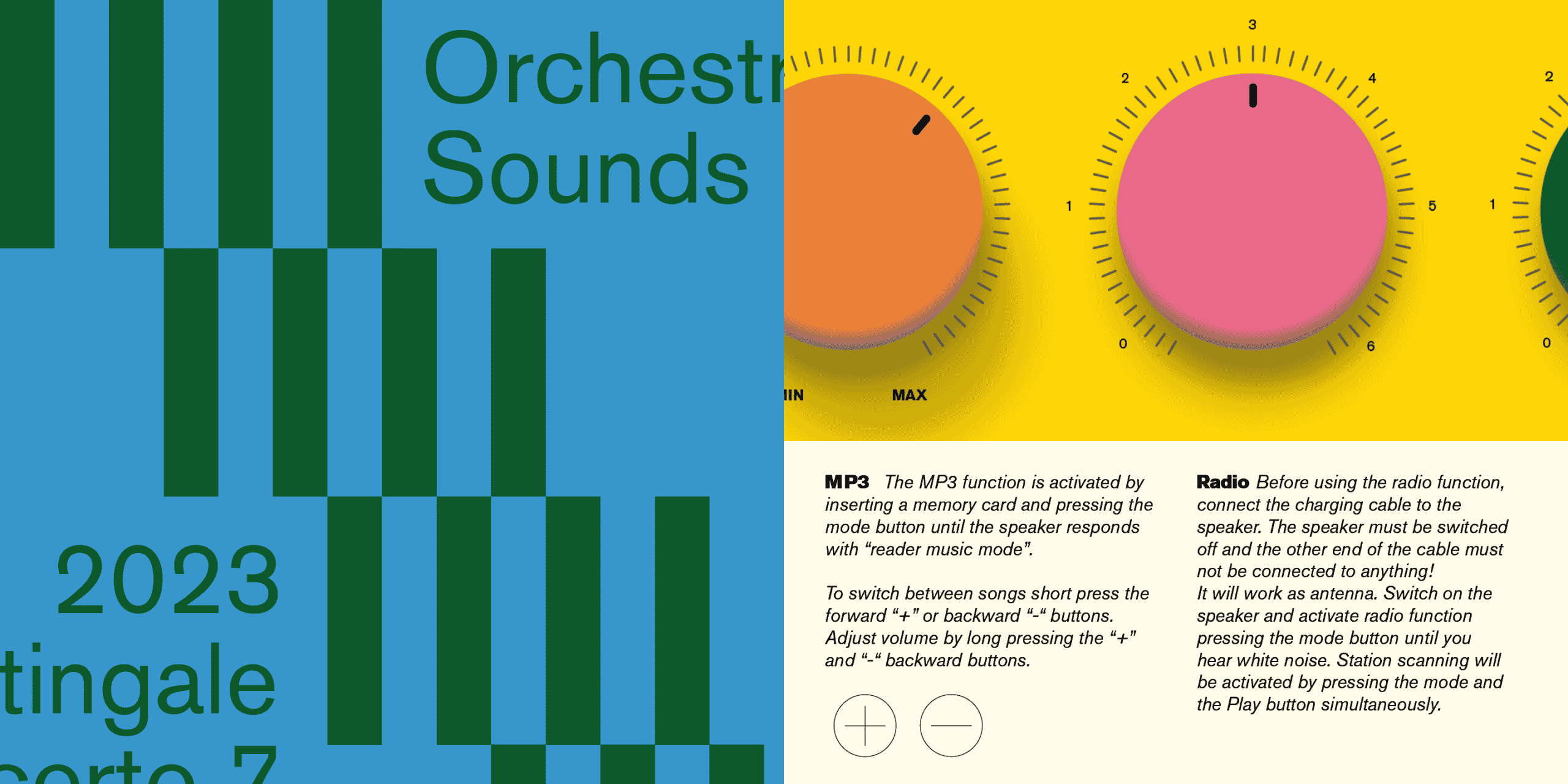
Monotype erwirbt Bertholds renommierten Schriftarten-Bestand – Mit diesem Schritt erweitert Monotype sein Angebot u.a. mit der weit verbreiteten ersten serifenlosen Schrift der Welt, Akzidenz-Grotesk, sowie um über 700 weitere historische Schriften aus der Traditions-Bibliothek mit Berliner Wurzeln. Und stellt damit Kreativen global eine noch umfangreichere Kollektion innovativer und gut gestalteter Typefaces zur Verfügung.
Die ursprüngliche Berthold-Foundry H. Berthold AG wurde 1858 in Berlin von Hermann Berthold gegründet und erlangte schnell weltweit einen Ruf für die Herstellung hochwertiger Schriften. Im Jahr 1997 erwarb Berthold Types Limited aus Chicago den gesamten Bestand sowie die Vertriebsrechte und die Wartung der digitalen Schriften. Bekannt ist die Berthold-Bibliothek vor allem für ihre berühmte und weit verbreitete Schriftfamilie Akzidenz-Grotesk, eine der ersten serifenlosen Schriften der Welt, die viele spätere Schriftentwürfe wie etwa Helvetica inspirierte. 1896 geschaffen wird die Akzidenz-Grotesk von zahlreichen der größten internationalen Marken verwendet. Neben diesem Kronjuwel umfasst der Bestand von Berthold auch viele weitere beliebte Schriften wie Imago, Cosmos, Formata, Block, Solemnis und City.
Ninan Chacko, CEO: „Mit diesem Kauf erhöhen wir die weltweite Sichtbarkeit der Berthold-Schriften, feiern ihr Erbe und bringen sie in die Hände von noch mehr Kreativen. Darüber hinaus stellt der Erwerb sicher, dass ikonische Schriftfamilien wie Akzidenz-Grotesk, Imago und Formata genauso zugänglich und relevant bleiben wie andere historische Schriftfamilien in der Monotype-Bibliothek, z.B. Helvetica Now, Gotham oder Neue Frutiger.“
Deb Gonet, VP Monotype Studio: „H. Berthold AG hat sich einen Namen unter den größten und erfolgreichsten Schriftbibliotheken gemacht und ist für ihre hochwertigen Schriften bekannt. Mit der Aufnahme dieser klassischen Bibliothek in unser Monotype Fonts-Angebot kommen wir unserem Ziel näher, Kreativen die beste und größte Auswahl an Schriften an einem Ort zu bieten.“